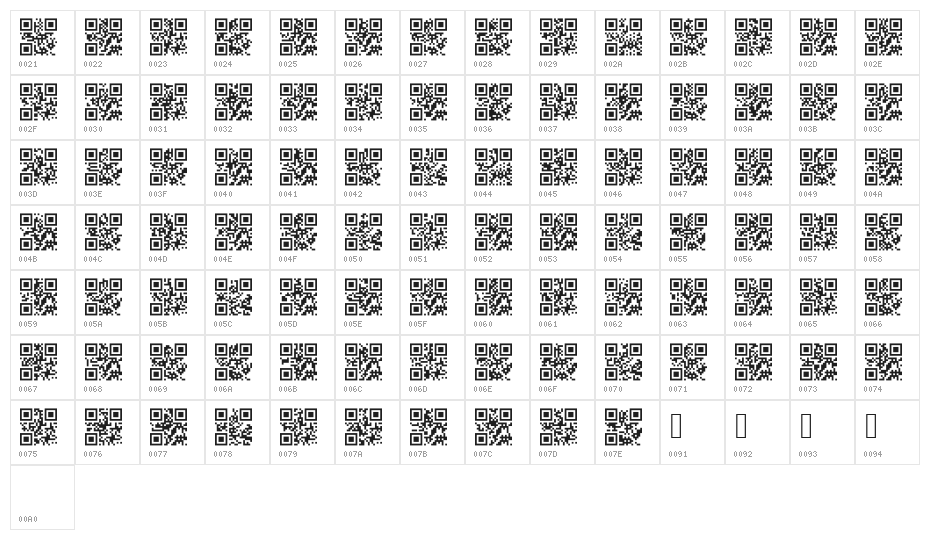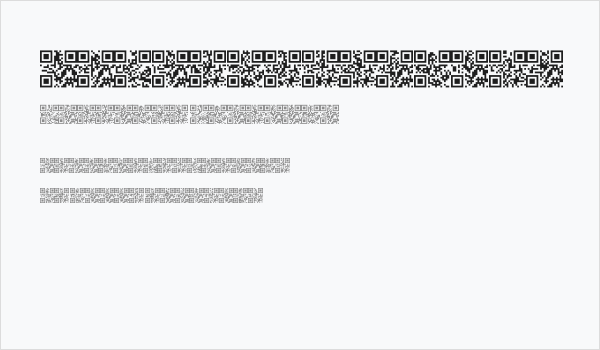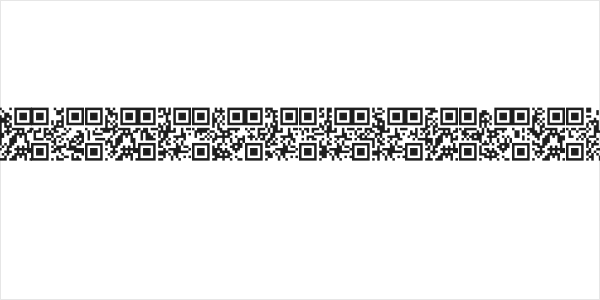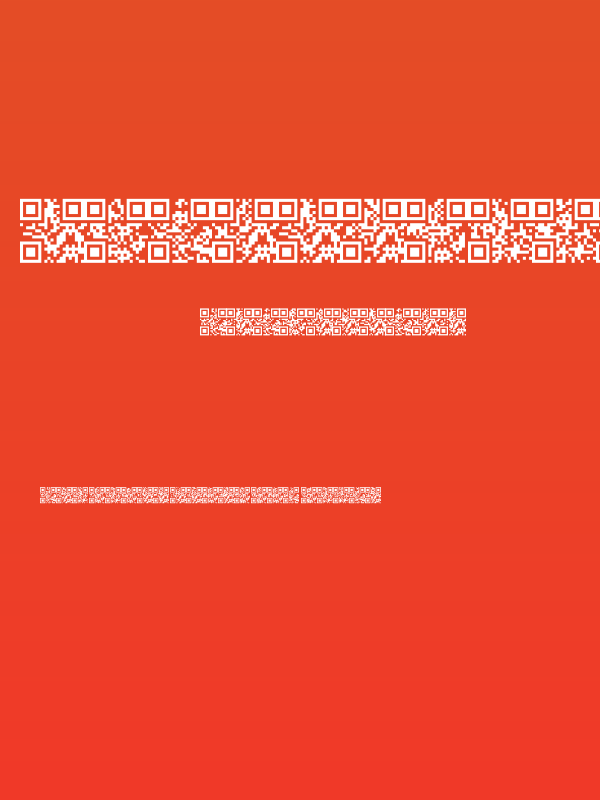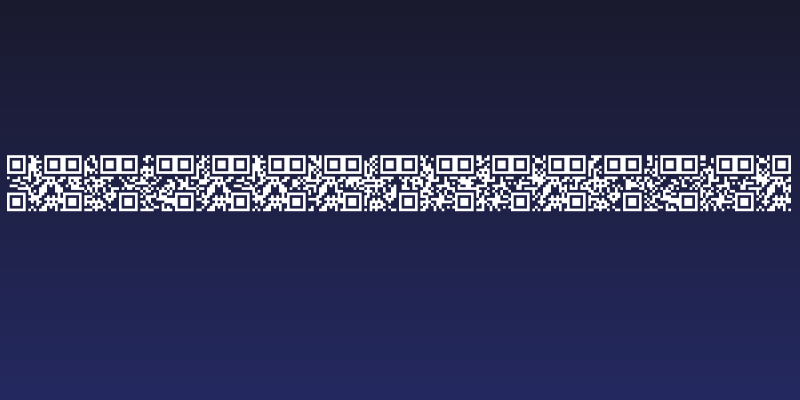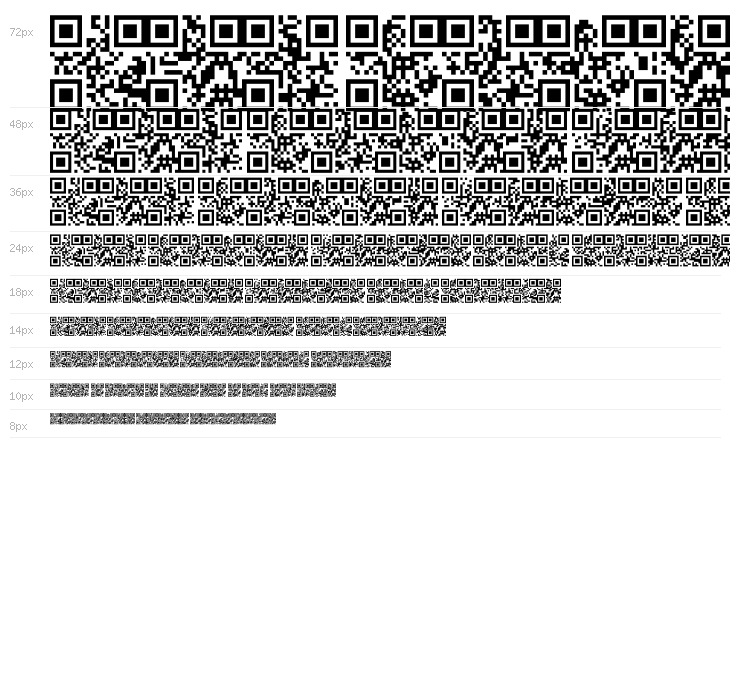
AlphanumericQR Font
| Stile generale | Modern, Tech-inspired, Experimental |
| Caso d'uso | Logos, Digital art, Machine-readable text, Tech branding |
| Progetti proposti | Data encoding, digital art, cryptography, machine-readable labels, tech branding. |